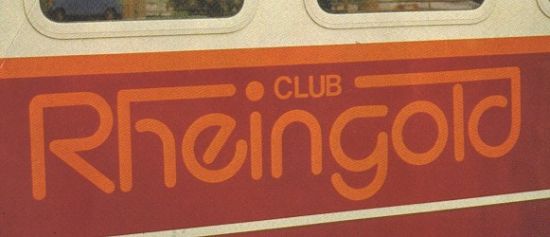
suche Schriftart(en) vom "Rheingold-Club" der ex.
ob dieses hier überhaupt eine definierte Schrift ist weis ich nicht. Vielleicht ist sie eine modifizierte Schriftart. Genauer sind es ja zwei Schrifttypen.
CLUB und Rheingold.
Das der Streifen bei Rheingold vom h zum d hin zusätzlich eingefügt wurde dürfte wahrscheinlich sein.
Dieses prangte mal auf dem Clubwagen des legänderen Rheingold der Bundesbahn von 1983-86. In den Foren über Eisenbahn haben sich andere schon vergeblich versucht.
Mein einziger Gedanke war bisher die Expressa, leider trift sie es nicht wirklich.
wenn es kein fest definierter Schrifttyp ist könnte man sich an Expressa orientiert haben.
Aber nur vielleicht.
So mein zweiter versuch:
wie wäre es mit "Planet Sans". Auch wenn dieser Font dafür ein paar Umbauten bräuchte, so könnte er es durch aus sein. Die nötigen Änderungen wären sehr schnell gemacht.
habe mir Planet Sans angeschaut. Vom e aus mal abgesehen durchaus möglich. Bleibt leider auch nur eine Vermutung.
Wird wohl nicht wirklich geklärt werden können.